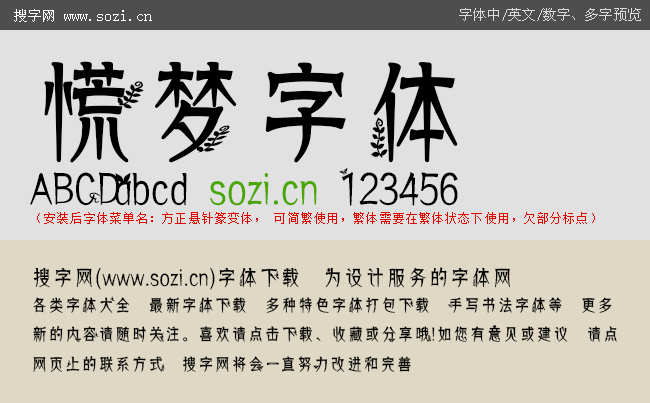
慌夢字體
搜字網(wǎng)給大家提供一款慌夢字體手機(jī)中文字體下載。這款手機(jī)字體是在方正懸針篆變簡體筆畫間插入了花紋圖案。方正懸針篆變字體意在保留篆書韻味,同時(shí)將隸書與楷書筆畫特征熔于一爐,實(shí)為三種書體的統(tǒng)一。將傳統(tǒng)書法藝術(shù)與現(xiàn)代形式語匯融合,追求裝飾性及藝術(shù)美感,端莊秀美、開張疏朗,雍容大氣、復(fù)古卻易讀。加入了卡通圖案后又增添了趣味性,特別適合喜歡手機(jī)字體個(gè)性一些的朋友在手機(jī)上安裝使用。